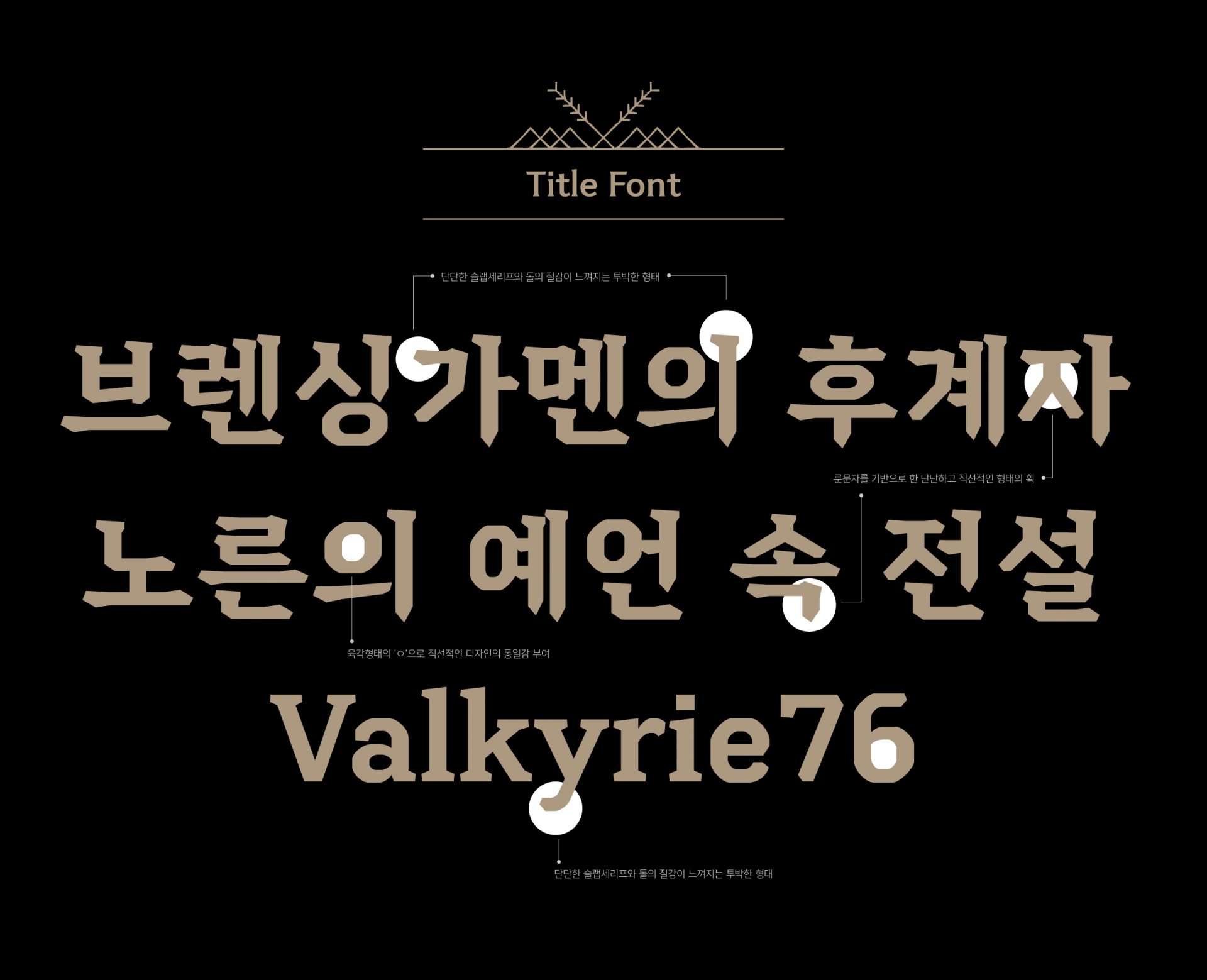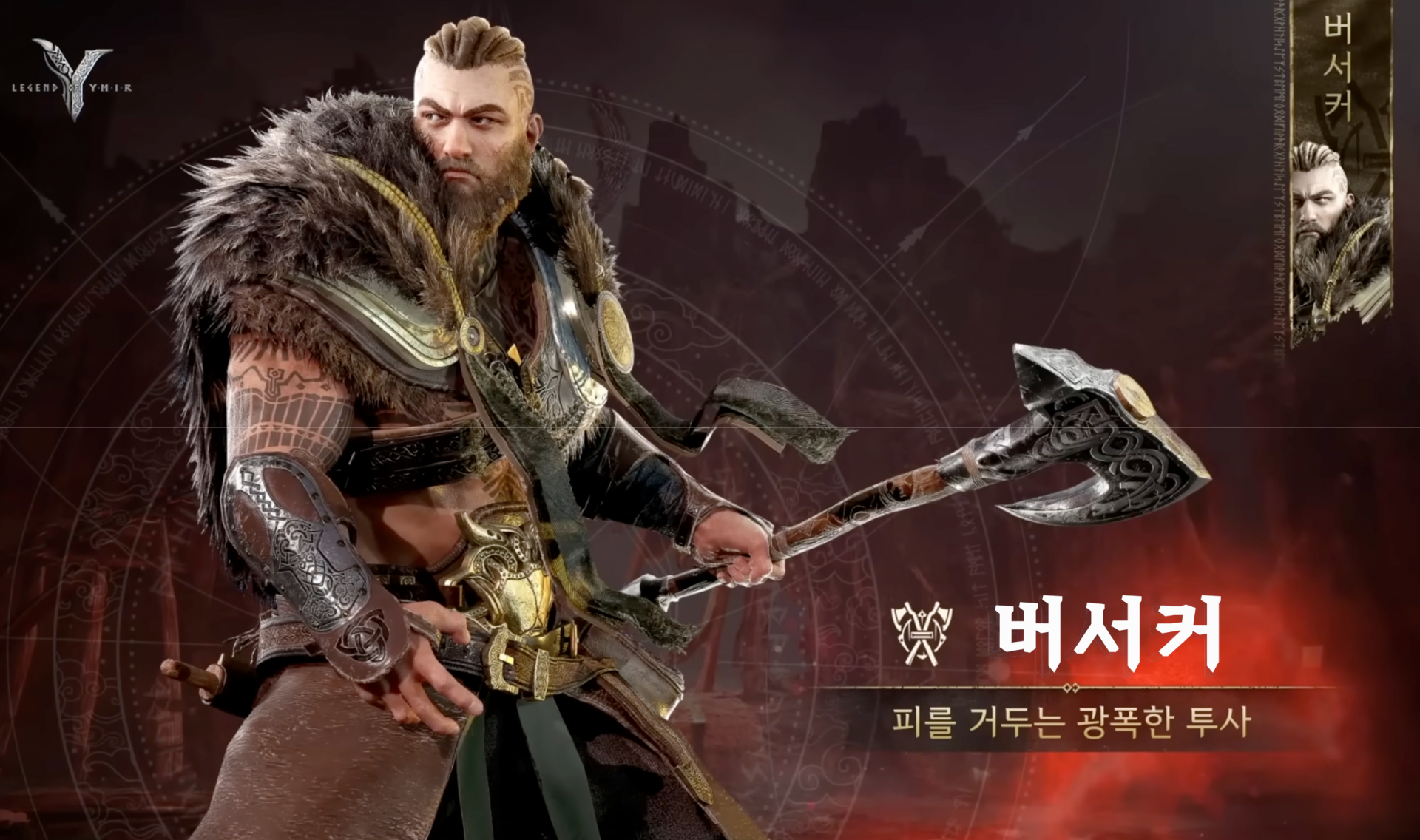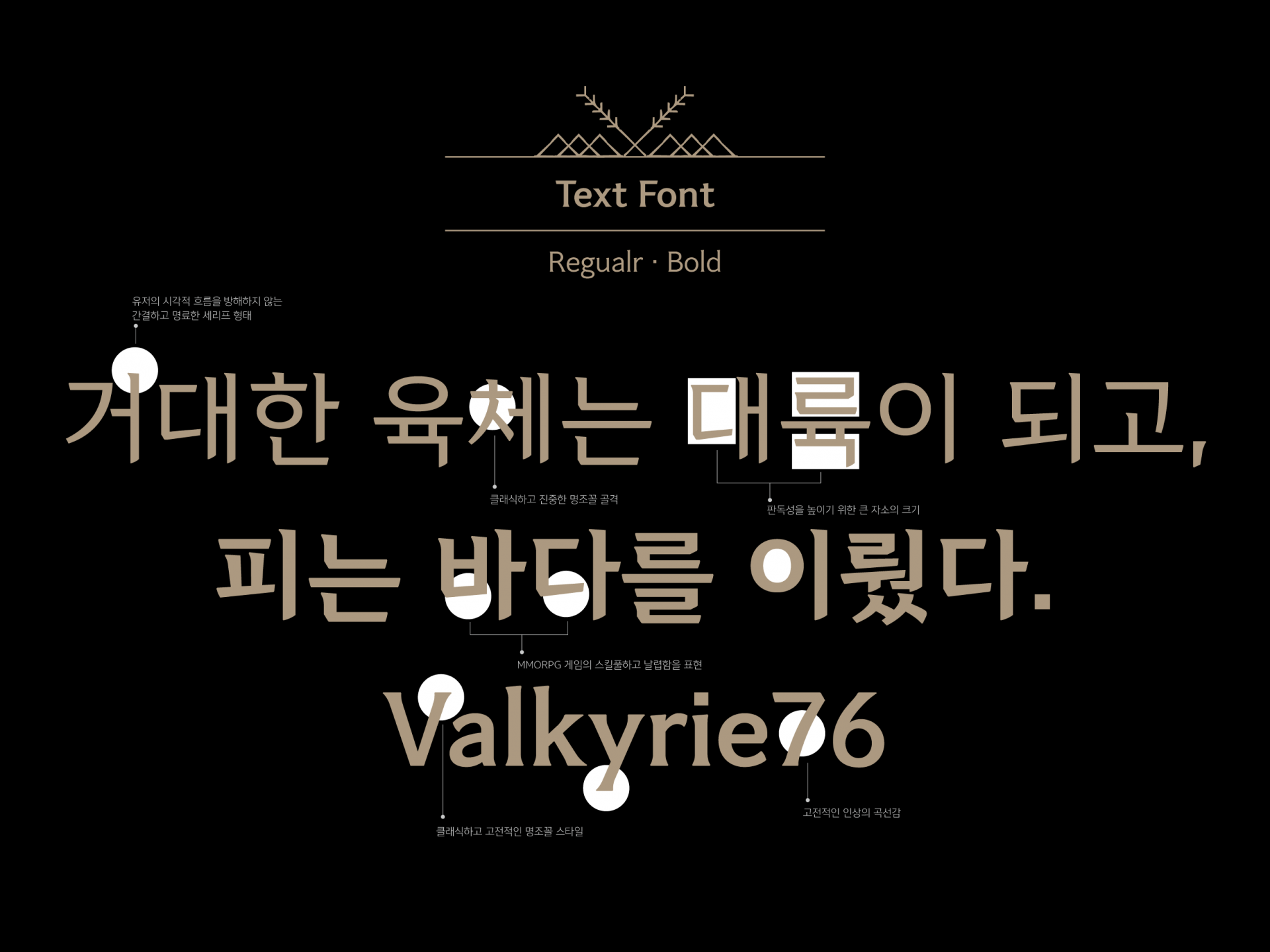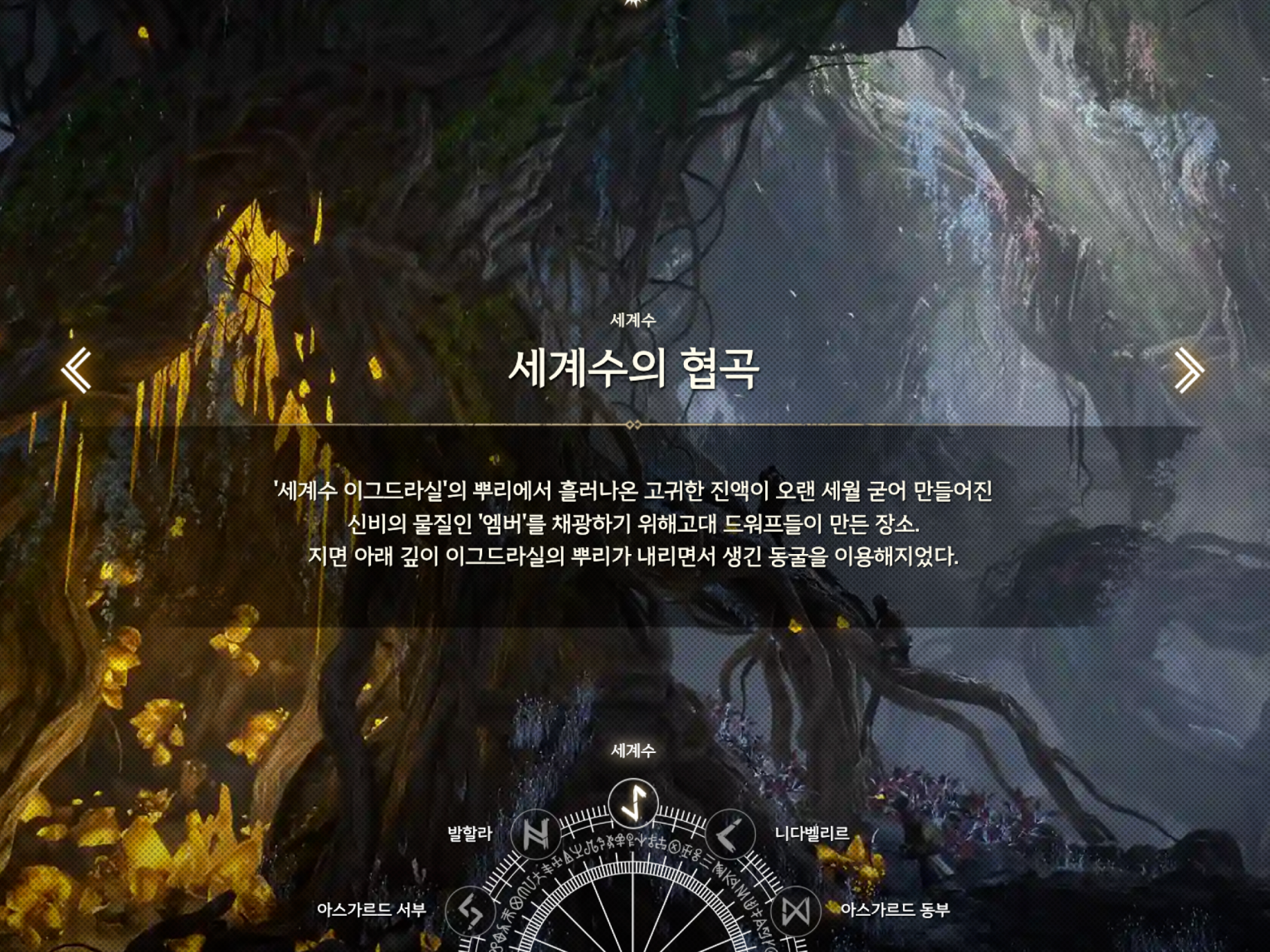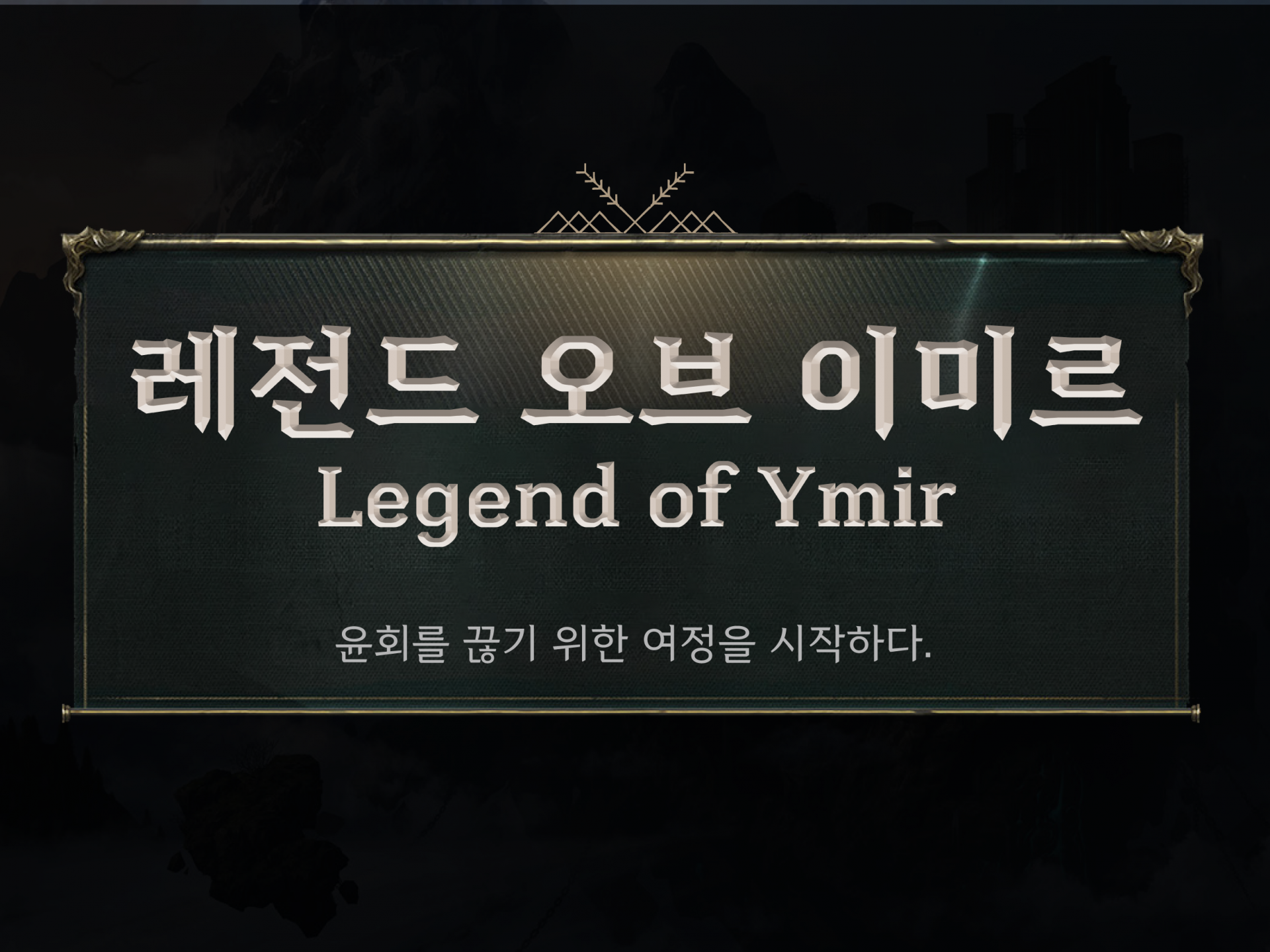
위메이드 [레전드 오브 이미르]
격동의 땅이자 태초의 거인 이미르의 이미지를 담아낸 서체이다. 룬문자를 모티브로 하여 현대적인 조형감을 가미하였으며, 돌으로 새긴 듯이 직선적인 이미지가 강하며 단단한 슬랩세리프와돌의 질감이 느껴지는 투박한 장식으로 고대의 이미지를 전한다.